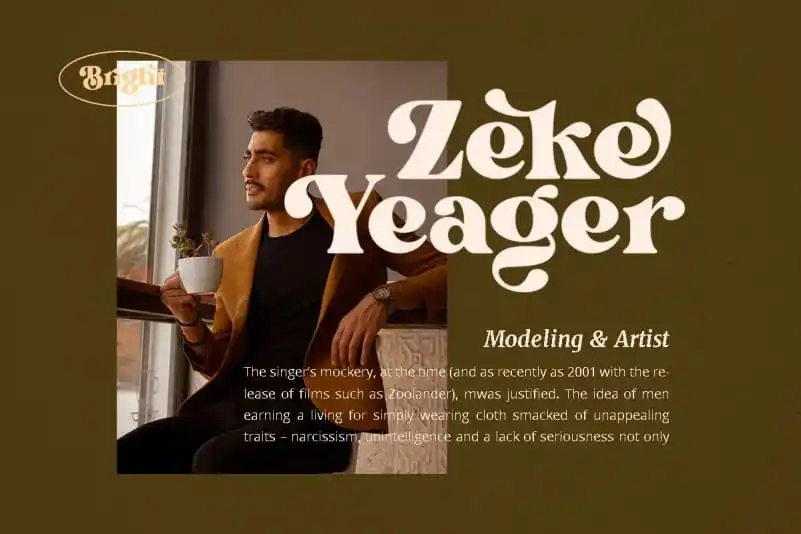
A Bright Serif Font é uma opção perfeita para quem busca um tipo de letra com um toque elegante e moderno. Desenvolvida pelo estúdio Dharmas Studio, esta fonte serif oferece um impacto firme e sofisticado em qualquer projeto de design que você esteja trabalhando. Ela combina elementos modernos e retro, resultando em uma aparência clara e divertida. Esta elegante fonte é perfeitamente adequada para projetos de design dos anos 60 ou 70, ajudando a criar layouts interessantes e divertidos que remetem a esse período nostálgico do design gráfico. Se você está procurando por uma fonte serif moderna e sofisticada, então esta é uma ótima escolha para sua próxima criação de design.